Branding dan Desain: Font dan Warna Mana yang Terbaik untuk Situs Web Anda?
Diterbitkan: 2022-07-18Dalam dunia branding, situs web adalah real estat online yang penting. Perlu segera memberi tahu pengunjung jenis merek Anda, apa yang Anda jual, dan cara membeli dari Anda. Banyak dari ini bermuara pada desain situs web — dengan font dan pilihan warna menjadi elemen kunci.
Tidak yakin bagaimana memilih font dan warna yang tepat untuk situs web Anda? Maka posting ini adalah untuk Anda.
Mengapa Pemilihan Font dan Warna yang Hati-hati Itu Penting
Ada banyak ilmu pengetahuan dan teori tentang bagaimana warna dan font mempengaruhi kita secara emosional dan menyampaikan pesan. Ada juga banyak pemikiran yang dimasukkan ke dalam bagaimana pilihan desain Anda dapat memengaruhi suasana hati, menimbulkan kepercayaan, dan membantu pemirsa untuk memahami apa arti merek Anda.
Inilah cara Anda menggunakan elemen-elemen ini untuk keuntungan merek Anda:
- Membangkitkan Emosi dan Sentimen
Selama berabad-abad warna telah digunakan untuk memancing respons dan membentuk hubungan. Orang Mesir, Isaac Newton, dan Carl Jung hanyalah beberapa tokoh sejarah yang mempelajari dan memanfaatkan kekuatan warna untuk menyebarkan pesan.
Warna yang Anda pilih akan berdampak besar pada perasaan orang saat menjelajahi situs web Anda dan kesan yang mereka dapatkan dari merek Anda.
Hari ini, diterima secara luas bahwa merah adalah peringatan dan bisa berarti bahaya, atau bisa berarti kegembiraan dan gairah. Biru menenangkan dan menenangkan, menimbulkan rasa percaya—bayangkan saja berapa banyak bank dan penyedia layanan keuangan yang menggunakan warna biru dalam branding mereka. Hijau sering berarti pergi, dan itu terhubung ke Bumi dan terkait dengan pertumbuhan, regenerasi, dan kehidupan baru.
Warna juga dapat menarik perhatian elemen penting seperti tombol Call To Action (CTA). Demikian pula, font dapat membangun sentimen tertentu untuk merek dan situs web. Semakin kreatif fontnya, semakin aneh tampilan sebuah merek. Di sisi lain, semakin sederhana fontnya, semakin korporat dan profesional situs web akan muncul.
- Memberikan Keterbacaan yang Baik
Keterbacaan adalah komponen penting dari desain situs web. Bagaimanapun juga, situs web merek Anda adalah alat fungsional yang perlu menyampaikan informasi penting kepada semua pengunjung. Pilihan warna dan font yang buruk dapat menyebabkan pengalaman pengguna yang buruk, meningkatkan rasio pentalan Anda, dan mengurangi dampak situs web Anda.
Misalnya, warna yang tidak kontras dengan baik dapat membuat sangat sulit untuk membaca salinan online. Sebagian besar warna kuning ketika dipasangkan dengan putih tidak memiliki kontras yang cukup untuk menonjolkan yang satu dengan mudah dari yang lain. Terlalu banyak warna kontras tinggi juga dapat membuat desain sibuk dan tidak fokus, sehingga sulit untuk mengetahui ke mana harus mencari atau apa yang harus diklik.
Tentu saja, pilihan font juga akan berdampak besar pada keterbacaan. Psikologi font mengatakan bahwa semakin sibuk font, semakin lama waktu yang dibutuhkan otak manusia untuk menafsirkan apa yang tertulis. Sebagian besar, kita berbicara milidetik di sini. Tetapi ketika ada banyak informasi yang harus diproses, milidetik itu dapat membuat dampak besar pada pembaca.
Cara Menggambarkan Suara Merek yang Berbeda
Saat mendesain situs web, penting bagi Anda untuk memikirkan suara merek dan siapa audiens targetnya.
Situs web untuk firma akuntansi akan memiliki tampilan dan nuansa yang sangat berbeda dari toko buku online yang mengkhususkan diri dalam novel untuk dewasa muda.
Jika kita melihat hanya pada firma akuntansi, desain untuk situs web tersebut dapat bervariasi dalam warna dan font berdasarkan pada siapa target merek—perusahaan multinasional besar atau pengusaha muda yang mengerjakan ide besar kedua atau ketiga mereka. Yang pertama akan membutuhkan font yang lebih serius dan palet warna yang membangkitkan kepercayaan, sementara yang kedua bisa menggunakan font yang lebih kreatif dan warna yang sedikit lebih berani yang menarik bagi rasa petualangan pengusaha muda.
Berikut adalah beberapa ide tentang bagaimana Anda dapat menggunakan font dan warna untuk membangun suara merek yang tepat secara instan untuk audiens target situs web:
- Potong Jelas Dan Profesional
Font sans-serif biasanya dikaitkan dengan merek perusahaan. Verdana, Calibri, Helvetica, dan Arial semuanya hebat dan dapat digunakan pada berbagai bobot untuk menciptakan penekanan dan hierarki dalam struktur konten Anda. Sifat langsung dari font ini segera membuat merek tampak profesional dan memudahkan pembaca untuk memproses informasi yang kompleks.
Untuk melanjutkan tampilan dan nuansa perusahaan, latar belakang putih sering kali menjadi pilihan terbaik. Ini membuat situs web tetap bersih dan mudah dilihat. Aksen dan warna kontras harus digunakan dengan hemat sehingga memberi dampak dan tidak mulai melengkung. Warna primer atau sekunder yang kuat sering kali paling cocok jika dipilih menggunakan metode pelengkap.
- Aneh Dan Kreatif
Di sinilah font skrip bisa ikut bermain. Juga dikenal sebagai font kursif, banyak dari mereka memiliki tampilan gambar tangan yang memberikan energi yang lebih kreatif. Berhati-hatilah untuk tidak terlalu berbunga-bunga karena salinannya menjadi lebih sulit untuk dibaca dengan semakin banyak baris yang Anda tambahkan ke setiap huruf. Skrip gothic yang terlalu mendetail, huruf gaya kaligrafi, atau font kerawang mungkin terlihat memukau tetapi tidak selalu berhasil, terutama jika Anda mempertimbangkan berapa banyak orang yang akan melihat situs web Anda di layar kecil perangkat seluler.
Jika Anda memilih font skrip, simpan untuk logo Anda dan mungkin judul Anda. Untuk font paragraf Anda, pilihlah sesuatu yang lebih dekat ke sans-serif karena ini akan membuat blok salinan besar lebih mudah dibaca.
Skema warna yang kreatif dan aneh sering kali paling cocok dengan warna sekunder atau tersier karena lebih lembut di mata. Anda juga dapat menggunakan latar belakang warna solid untuk situs web daripada latar belakang putih polos.
Menggunakan skema analog atau monokromatik adalah cara yang baik karena Anda dapat membawa berbagai corak warna untuk mencerahkan desain. Ini sangat baik untuk situs web portofolio yang digunakan materi iklan untuk memamerkan karya mereka dan apa yang dapat mereka tawarkan kepada klien.
- Akademik Dan Ilmiah
Font serif seperti Times New Roman dan Georgia sangat bagus untuk merek yang memiliki sifat ilmiah atau memberikan berita kepada publik. Font ini sama profesionalnya dengan font sans-serif tetapi pembaca berharap untuk melihatnya dalam keadaan yang sedikit berbeda. Orang lebih cenderung menemukan font serif yang dapat dipercaya dalam pengaturan akademik dan berita.
Jurnal dan surat kabar ilmiah biasanya cukup monokromatik dengan warna hitam dan putih untuk palet warnanya. Latar belakang putih dengan font hitam, dan satu warna aksen (seringkali merah) adalah tampilan tradisional. Anda kemudian dapat menambahkan lebih banyak warna dengan gambar yang sesuai dengan konten situs web dan informasi yang dipublikasikan.
Jadikan Warna dan Font Menghitung
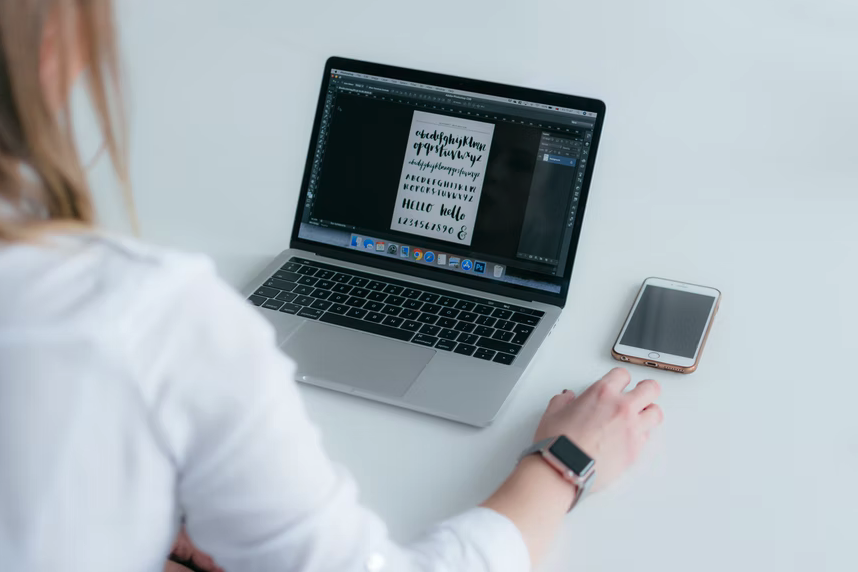
Tidak dapat disangkal. Warna dan font yang Anda pilih dihitung. Mereka dapat membuat atau menghancurkan situs web Anda dan merupakan bagian integral dari pengalaman pengguna. Dengan memilih warna yang mewakili nilai merek Anda, Anda dapat menciptakan kesan yang baik, dan menggunakan font yang menonjol akan memastikan bahwa semua orang tahu persis tentang diri Anda.
Dengan menggunakan tips di sini, Anda dapat memilih palet warna dan font yang paling sesuai dengan merek Anda. Setelah Anda selesai melakukannya, desain situs web Anda akan menyatu dengan mudah.